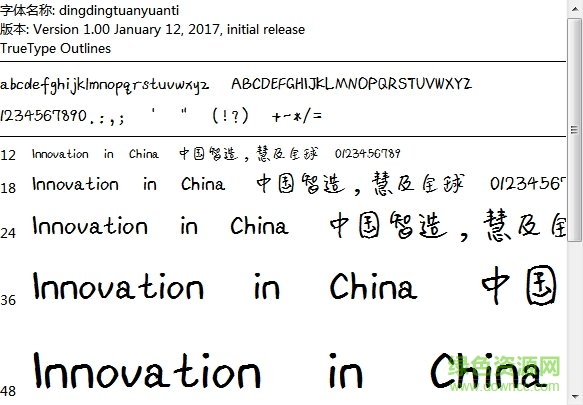
丁丁團(tuán)圓體ttf是丁丁系列的一款好看手寫(xiě)體,圓潤(rùn)可愛(ài)的筆觸,讓文字充滿了童真童趣的活潑體驗(yàn),間距比較大,讓你的內(nèi)容更好的表達(dá)和呈現(xiàn),綠色資源網(wǎng)獨(dú)家推薦!
丁丁團(tuán)圓體ttf象征著一種團(tuán)圓喜慶的氛圍,柔軟秀氣給你舒適的藝術(shù)美感,字里行間跳動(dòng)的都是令人倍感溫馨的喜悅,可以用于多種藝術(shù)設(shè)計(jì)行業(yè)。